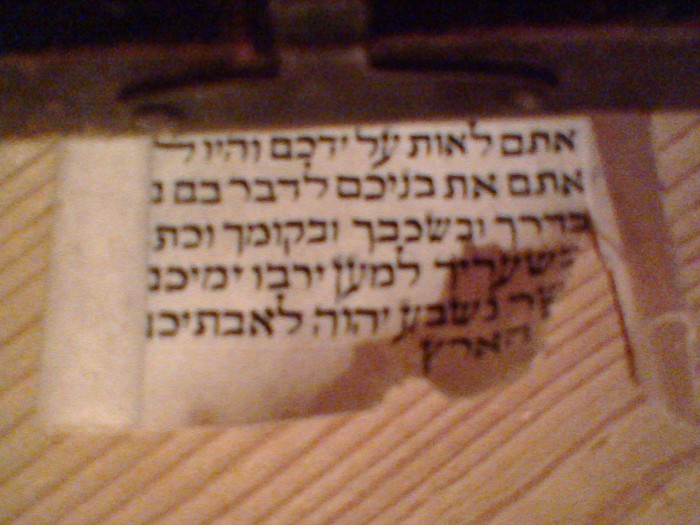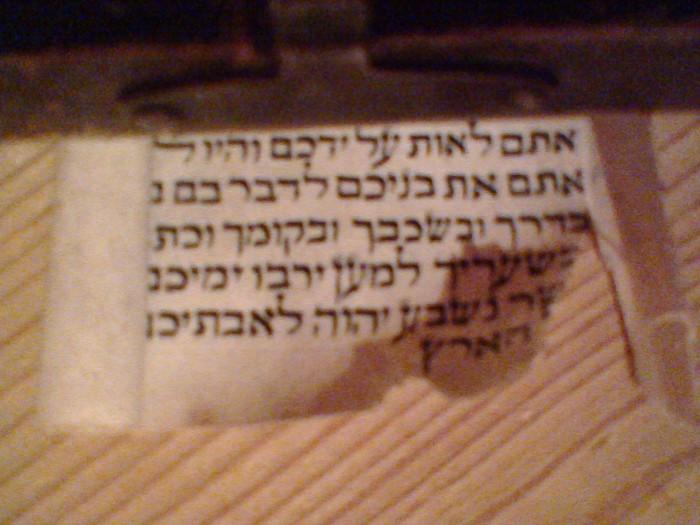
Glaub hab was seeehr altes gefunden
Hallo an alle, kann irgendjemand diese Schrift lesen?
Hab diese Rolle gefunden, schaut echt alt aus!post-32101-0-03677600-1439575919_thumb.j
Über das Alter kann ich nichts sagen. Es handelt sich aber um einen Textausschnitt aus der jüdischen Bibel / dem Alten Testament, die Schriftzeichen sind also Hebräisch (und zwar unpunktiert, d.h. ohne Vokale, die in bestimmten Bibelausgaben unter den im Bild sichtbaren Konsonanten stehen). Der Text beginnt mitten im 5. Buch Mose (oder Deuteronomium) Kapitel 11, Vers 18. Unter bibleserver.com kannst Du den folgenden Text in die Suchfunktion eingeben und Dir Übersetzungen der Passage anschauen:
אתם לאות על־ידכם
Wenn das tatsächlich etwas seeeehr altes ist, würde ich vorschlagen, damit mal zu einem passenden Museum bzw. einer Hochschule zu tingeln, damit sich das ein Profi ansehen und ggf. fachgerecht konservieren kann …